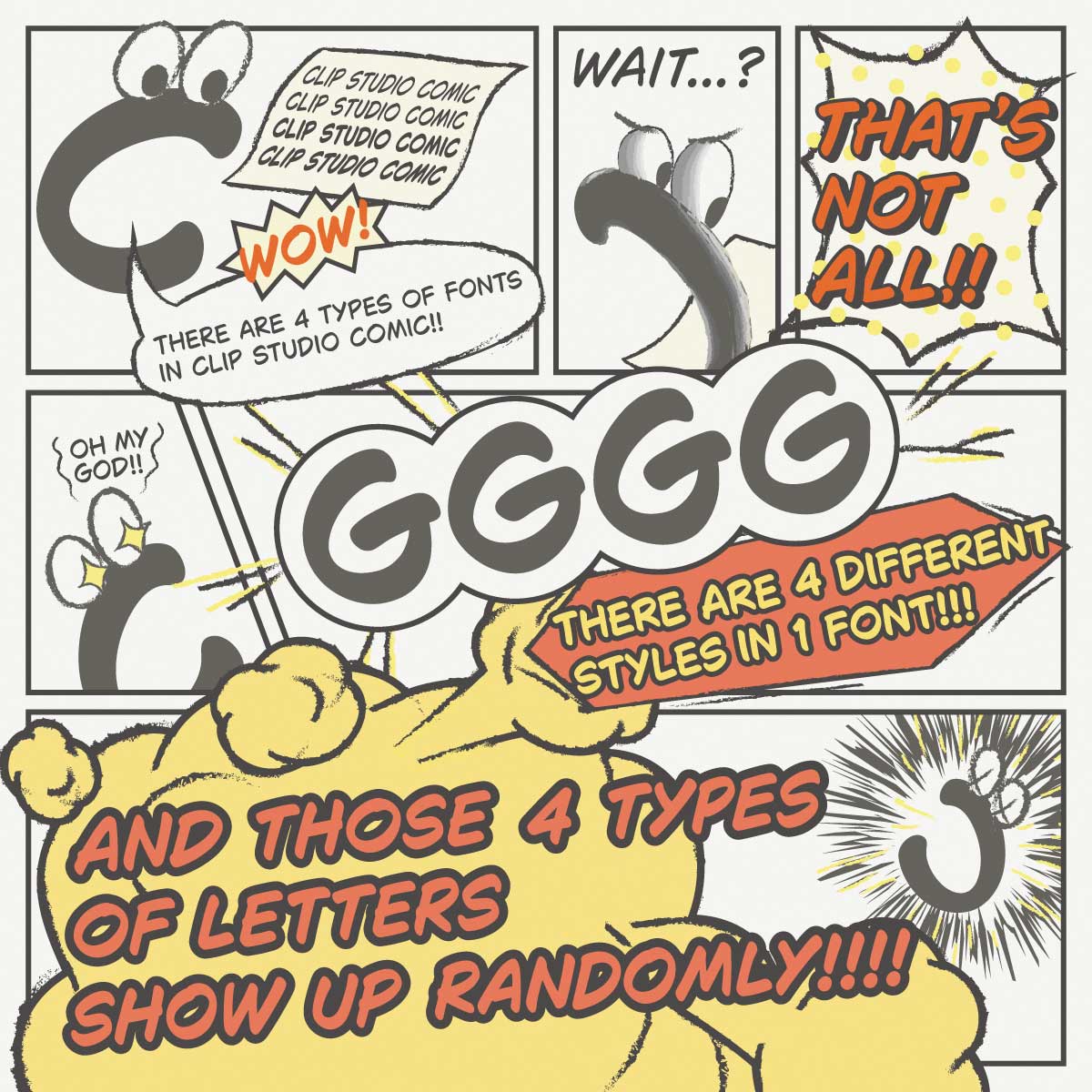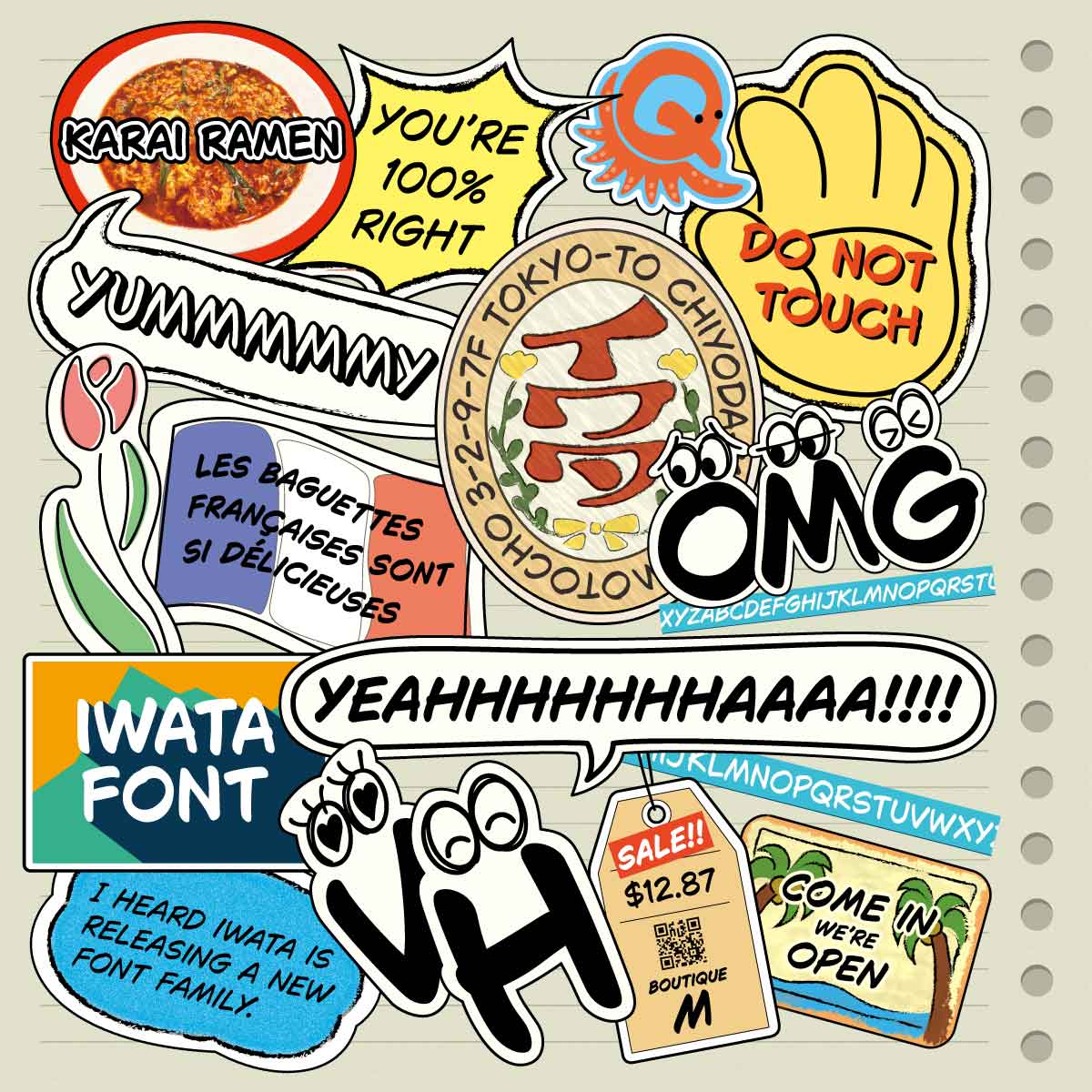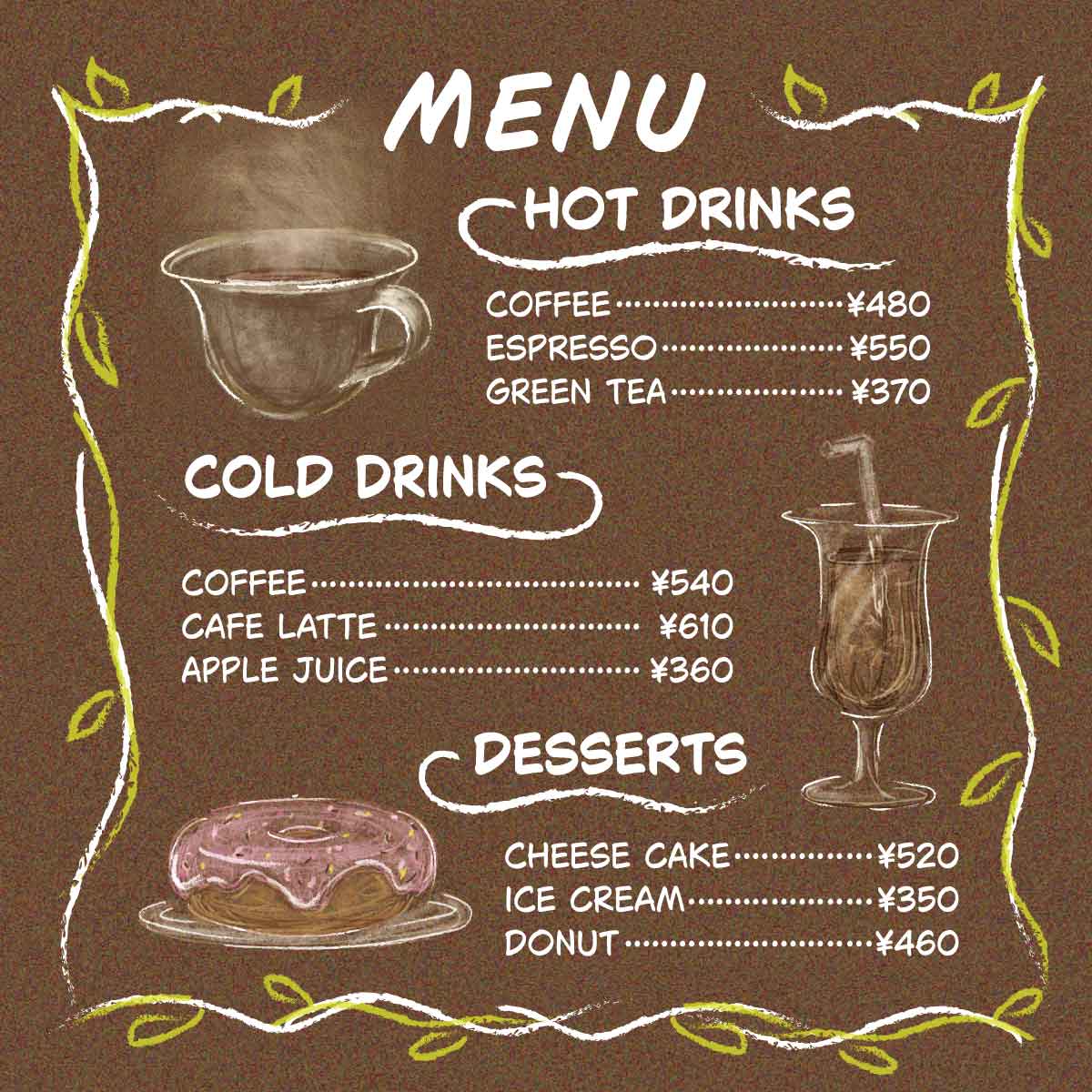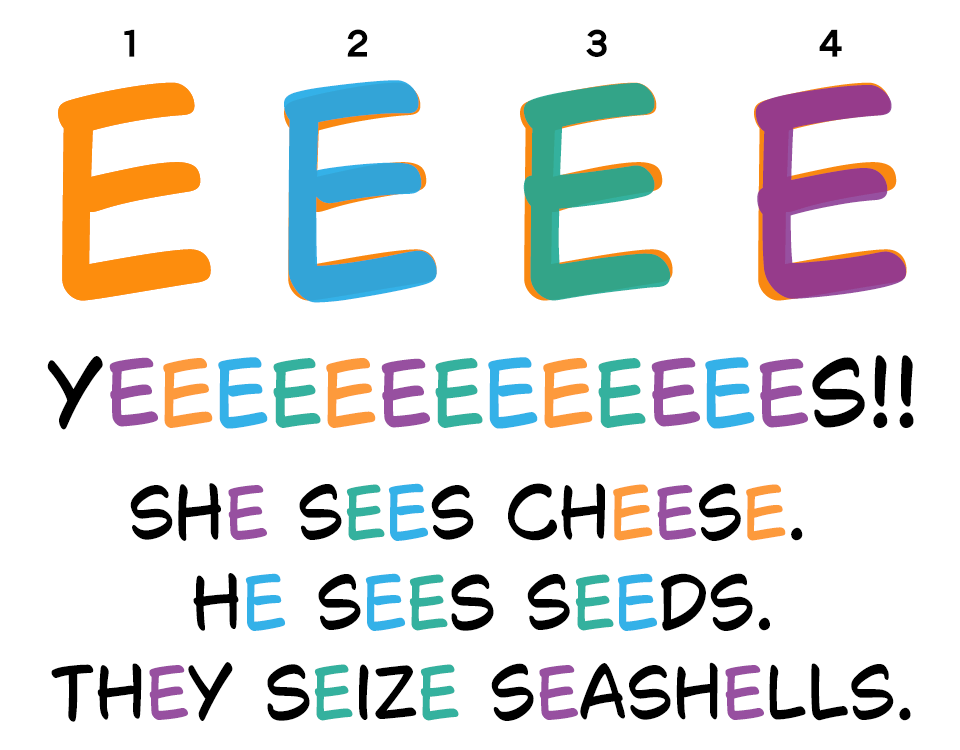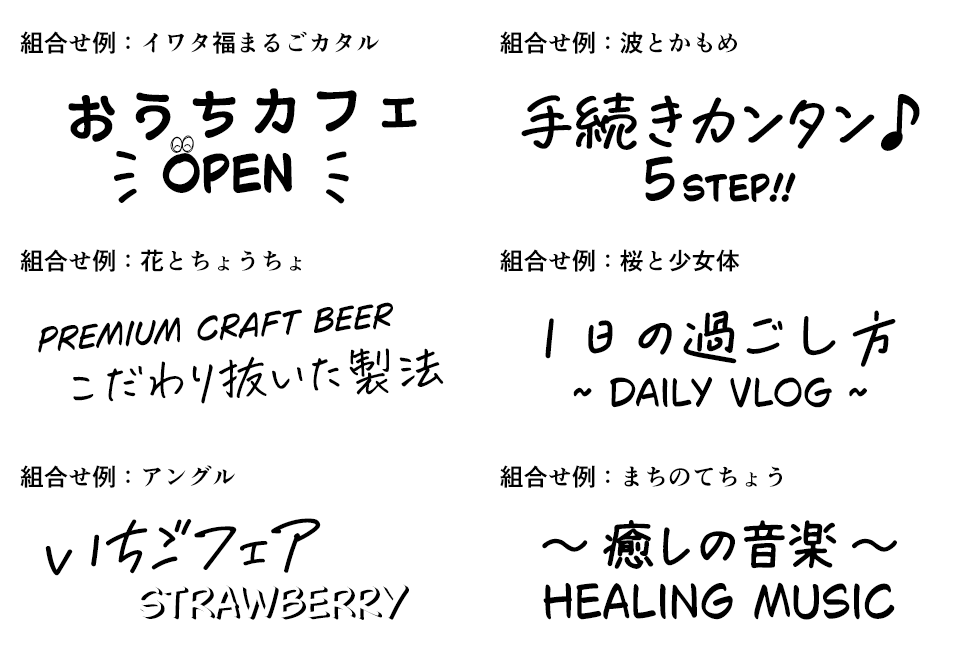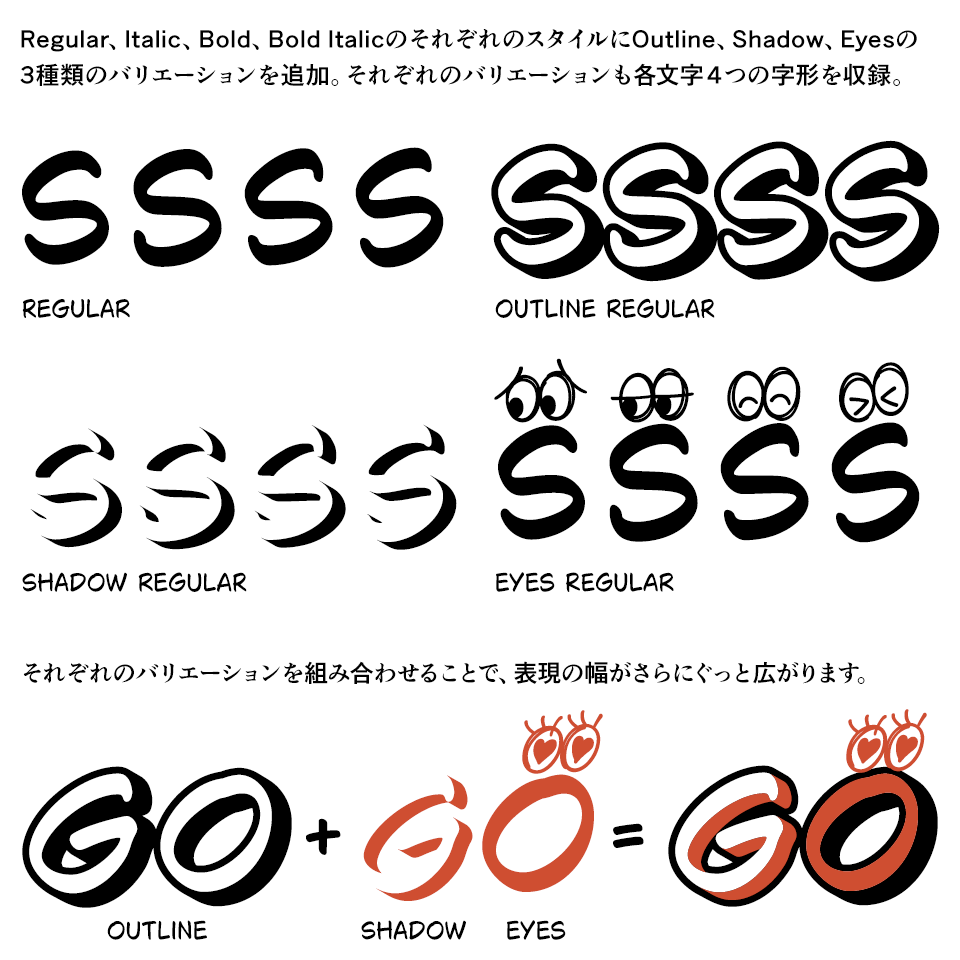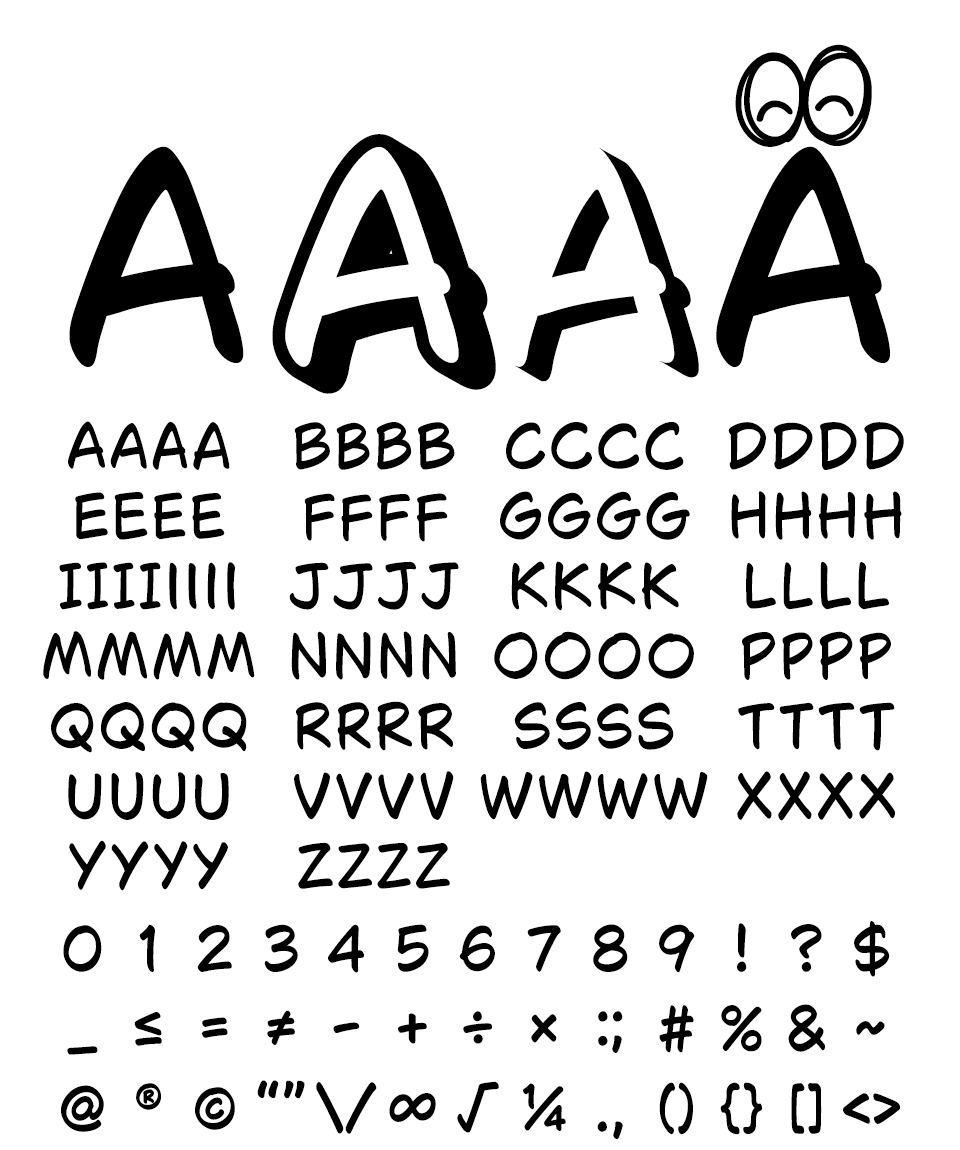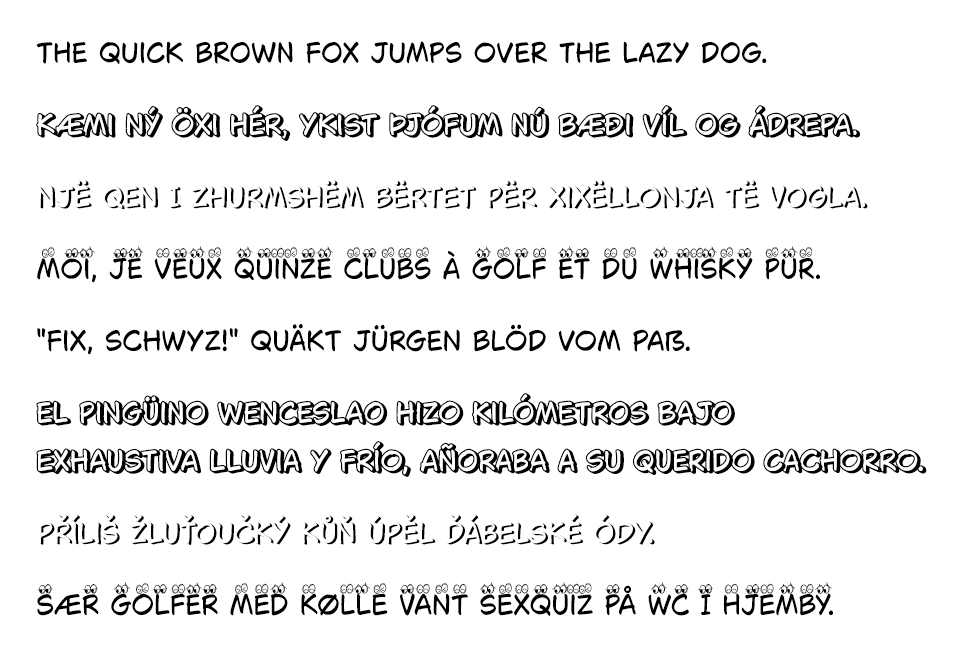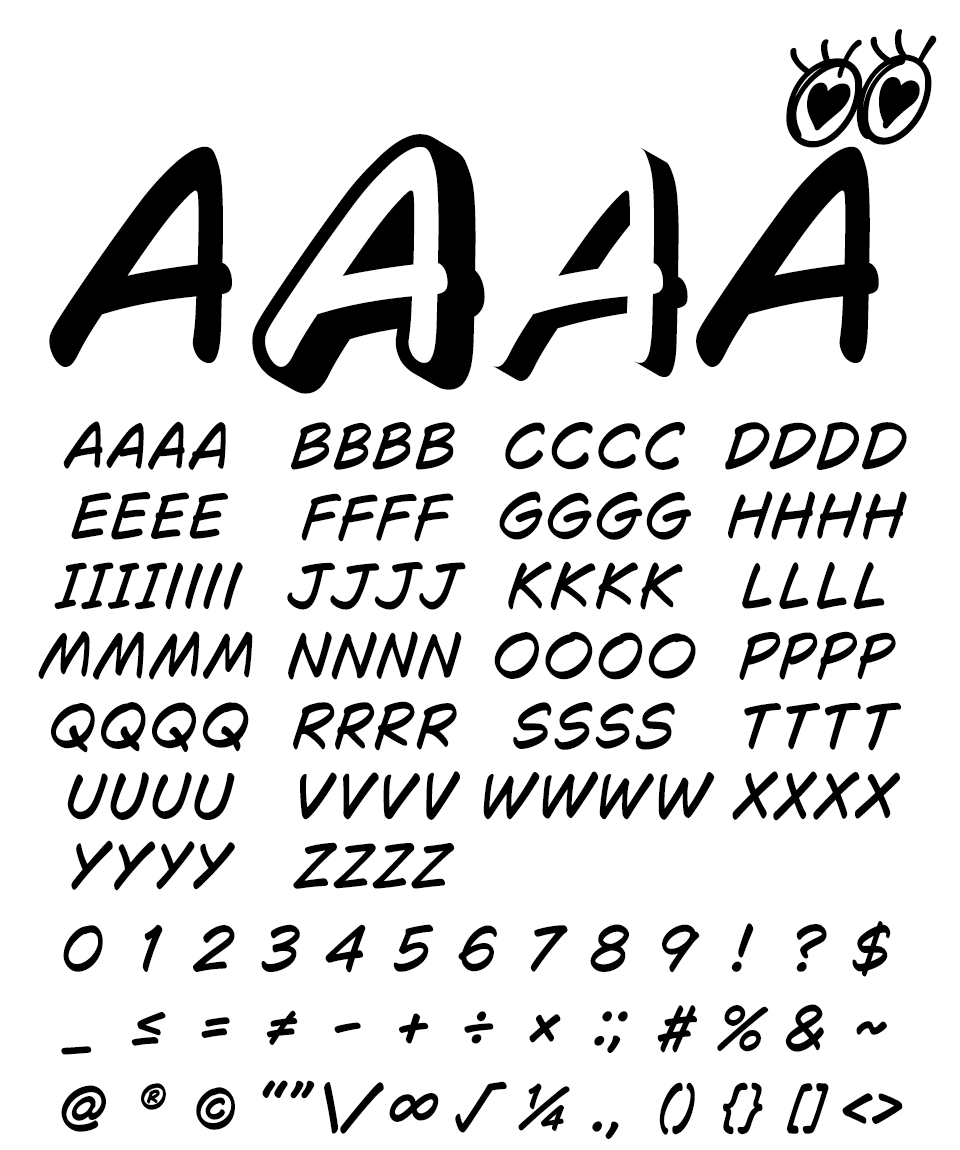
手書き風×自然なゆらぎ 感情が伝わる欧文フォント Iwata Clip Studio Comic
手書き風×自然なゆらぎ ── 感情が伝わる欧文フォント「Iwata Clip Studio Comic」
「Clip Studio Comic」は、イラスト・マンガ・Webtoon・アニメーション制作アプリCLIP STUDIO PAINTのVer.3.0以降に標準搭載されている、海外のマンガ制作現場で好まれる手書き風のフォントです。OpenTypeフォントの前後関係に依存する字形機能を活用した一文字ごとに表情を変えるランダム字形により、リアルな手書き感と可読性を兼ね備え、漫画のセリフやナレーションのテロップ、広告コピーなどに自然な“ゆらぎ”と感情をもたらします。
「Clip Studio Comic」の一般発売に合わせて、追加絵文字を収録し、さらにOutline、ShadowそしてEyesの3種類のバリエーションを追加し、さらに便利にさらにお得にパワーアップしたイワタDX版「Iwata Clip Studio Comic」も発売になりました。
漫画・アニメ業界だけでなく、SNSや同人誌・プレゼン資料・映像作品など、幅広い用途に対応。
「伝える」から「伝わる」へ──文字に感情を乗せたいすべてのクリエイターへ届けます。
「Iwata Clip Studio Comic」の概要
各文字それぞれに4つの字形を収録。
ラテンアルファベット圏の多くの言語表記をカバー
イワタDX版「Iwata Clip Studio Comic」は、CLIP STUDIO PAINT Ver.3.0以降搭載版のそれぞれのスタイルに収録グリフを追加し、Outline、Shadow、Eyesのバリエーション増やし大幅にパワーアップさせています。それでもお値段据え置き。さらに便利でさらにお得になった特別商品です。
「Iwata Clip Studio Comic」とは?
「Iwata Clip Studio Comic」ってどんなフォント
Iwata Clip Studio Comic イワタクリップスタジオコミック の制作風景
「Clip Studio Comic」は、書き文字のリアリティをフォントにしたCLIP STUDIO PAINT専用欧文フォントです。完全互換版の市販化に合わせて、絵文字やファミリーを増やした「Iwata Clip Studio Comic」が販売されました。書体開発初期のラフスケッチはCLIP STUDIO PAINTのブラシツールを使用して書き起こし、細部に至るまでリアルな手書き感にこだわって制作されています。
制作された株式会社イワタの坂口ゆかりさんに「Clip Studio Comic」についてお話を伺いました。
「Clip Studio Comic」を作ろうと思ったきっかけ
世界各国のエントリーユーザーからプロのクリエイターまで幅広く愛用されているイラスト・マンガ・Webtoon・アニメーション制作アプリ CLIP STUDIO PAINTでは、マンガの吹き出しなどに使われる「イワタアンチック体」がバンドルされています。
CLIP STUDIO PAINTの海外ユーザーがとても増えたため、海外ユーザーがコミックを作成する時に使えるオリジナルの欧文を作りませんかと営業部からご提案したのが始まりです。
【世界各国のクリエイターに向けた多言語に対応】
Iwata Clip Studio Comic イワタクリップスタジオコミック 多言語に対応!
「Clip Studio Comic」は、フランス語、スペイン語、ドイツ語、イタリア語などラテンアルファベット圏の多くの言語表記をカバーしています。